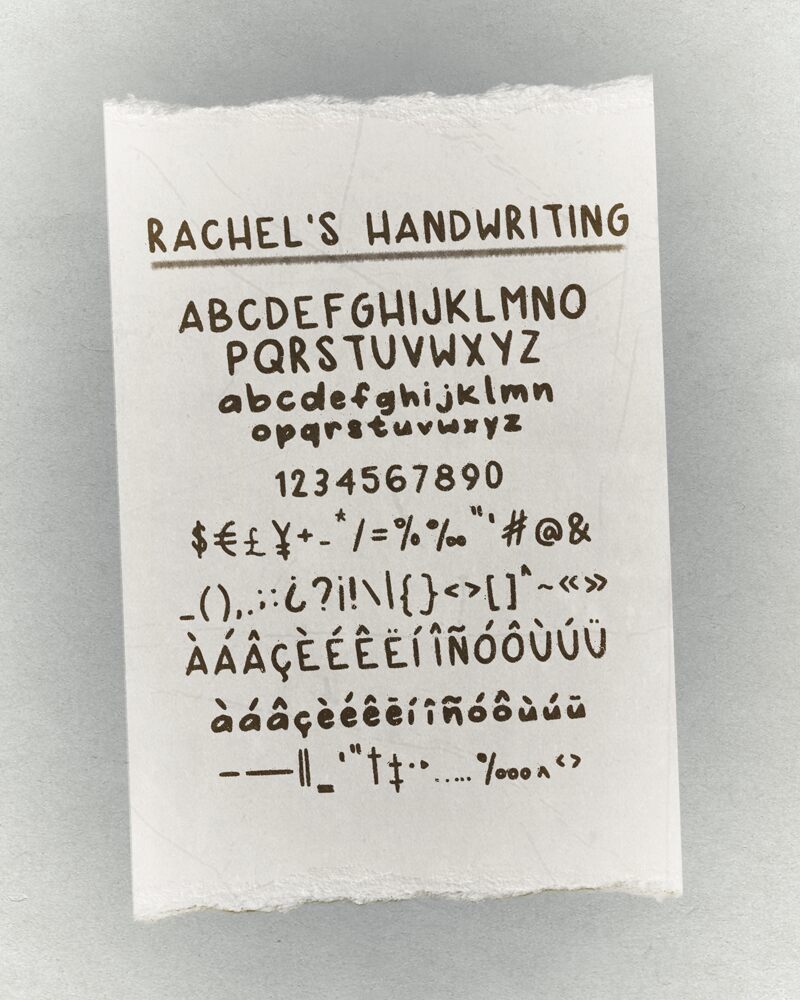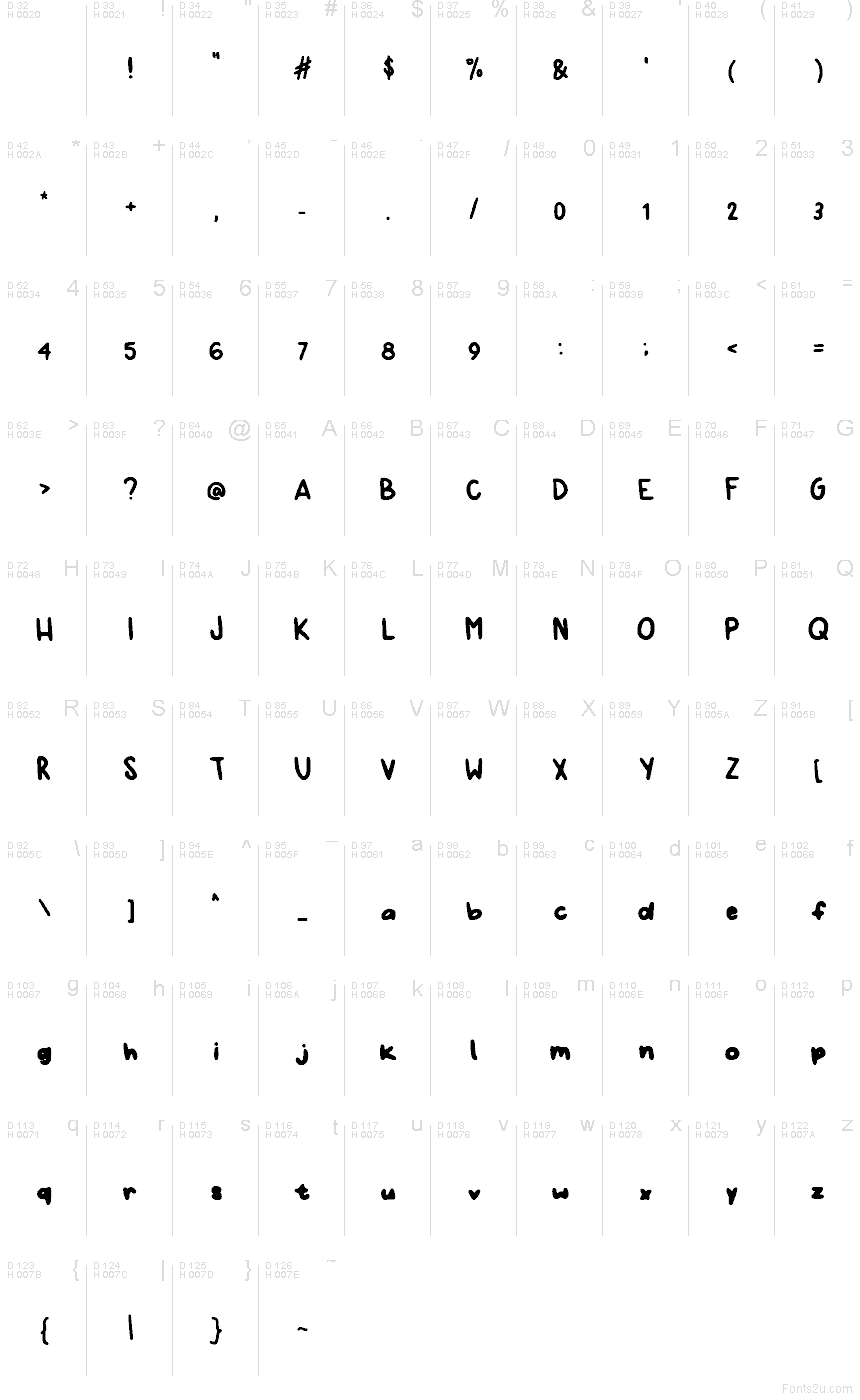
Il font Rachels Handwriting di Rachel Tong è una scrittura a mano gratuita che trasmette il calore e la naturalezza di un pennarello spesso sulla carta. I tratti sono pieni e arrotondati, con una spaziatura amichevole e quel pizzico di irregolarità che la rende autentica e personale: proprio come un appunto veloce attaccato al frigo, non un carattere studiato a tavolino.
Usa Rachels Handwriting per sticker, schede didattiche per bambini, poster per la classe, pagine di diario, caption per i social, etichette di prodotti, dettagli sul packaging e titoli allegri per rendere i tuoi progetti caldi e accoglienti. Impostalo con una dimensione leggermente più grande per far respirare il suo tratto audace e abbinalo a un carattere sans serif pulito per il testo principale, così da mantenere il layout ben leggibile.
Rachels Handwriting
Rachel Tong